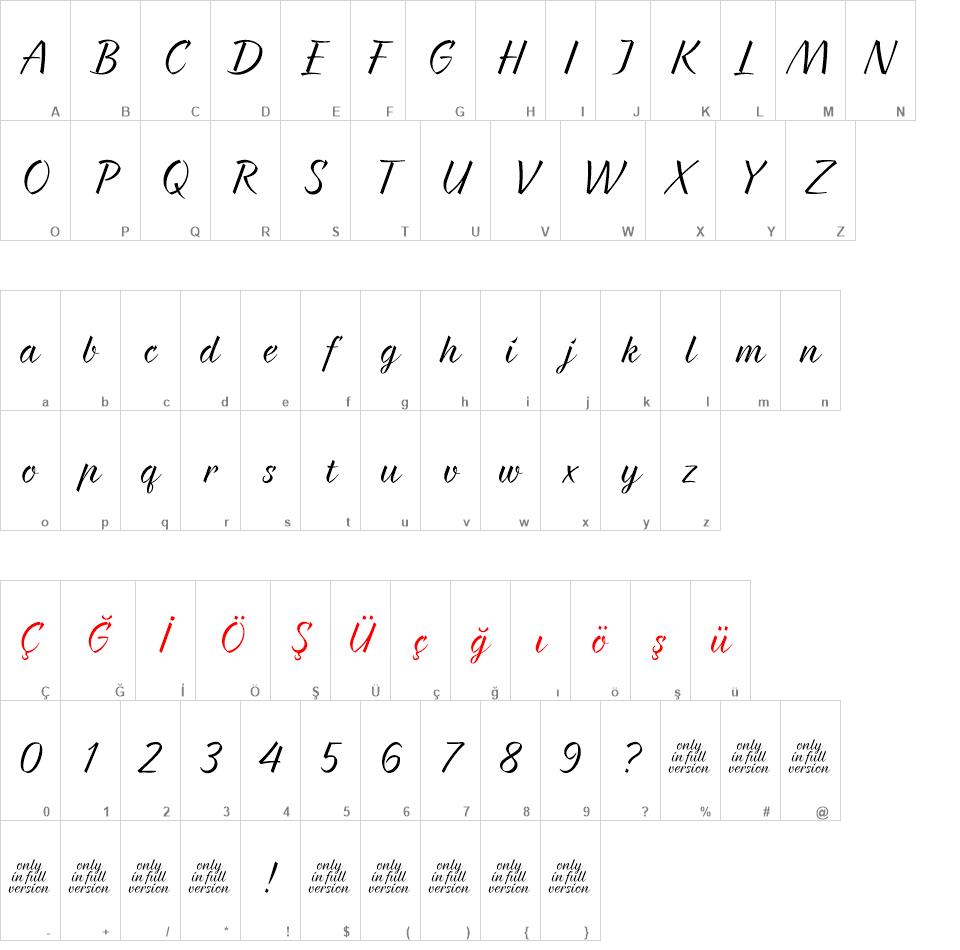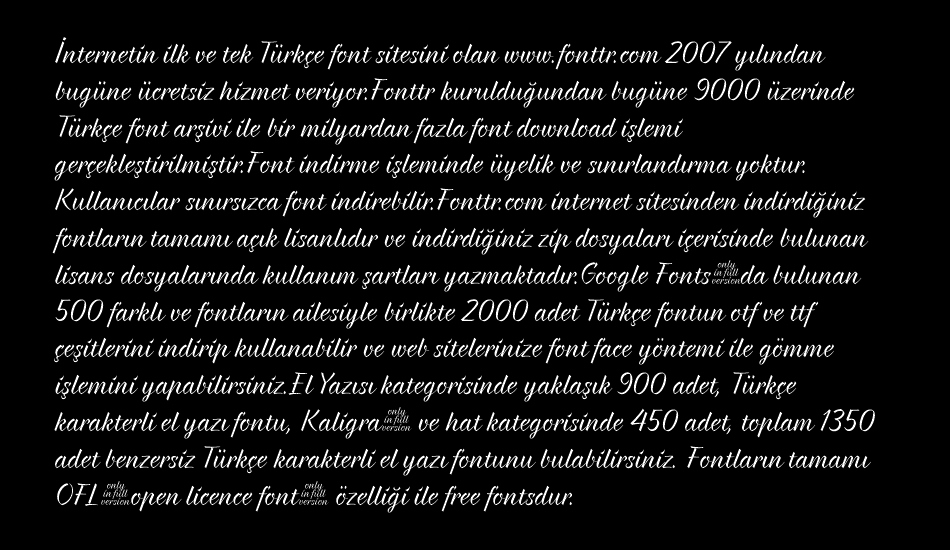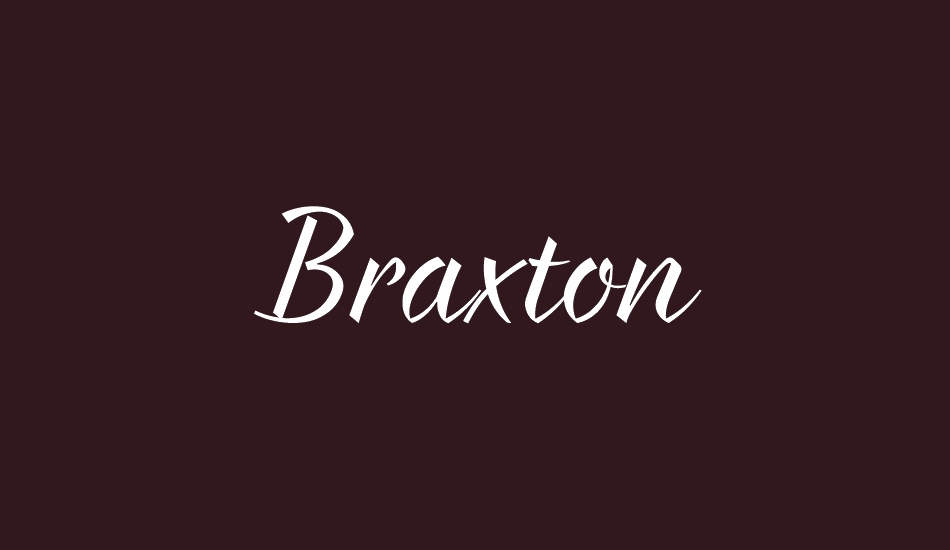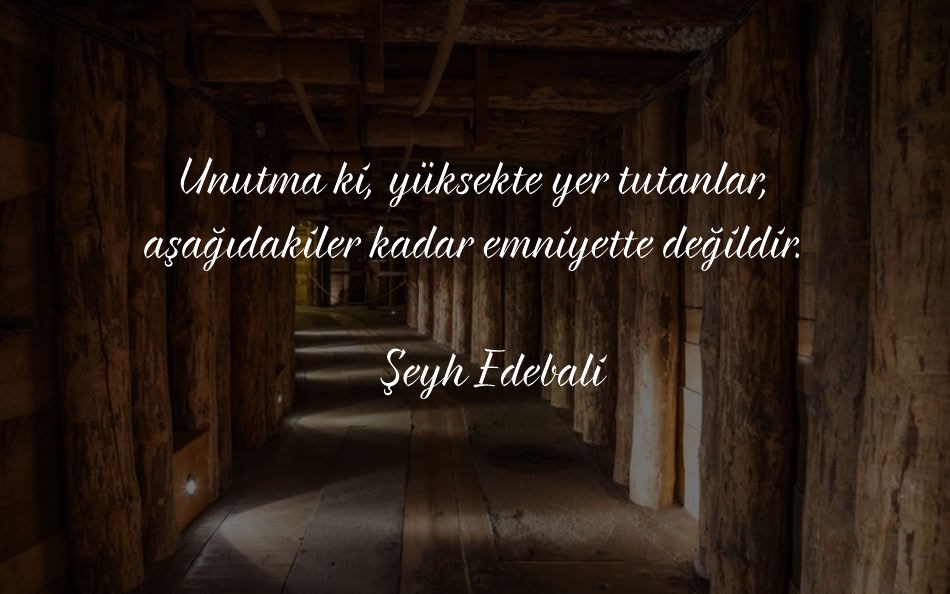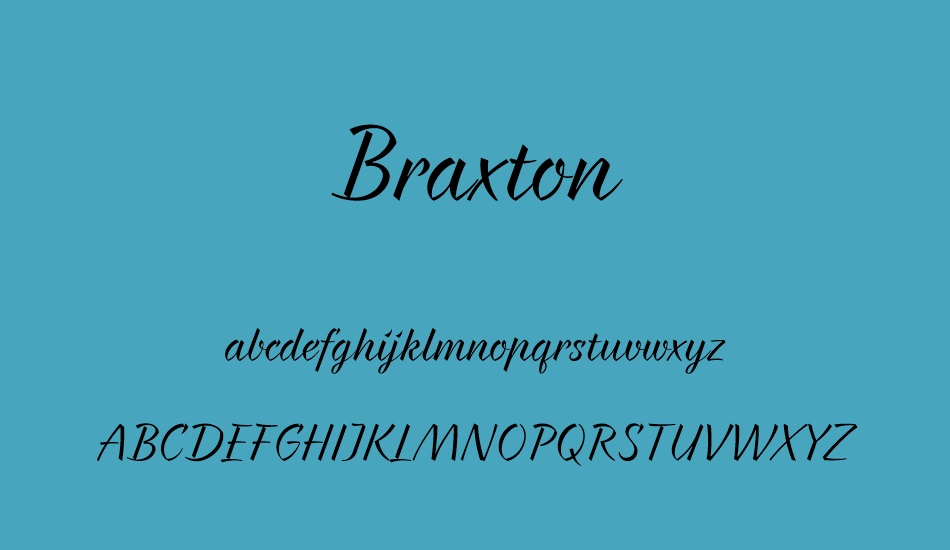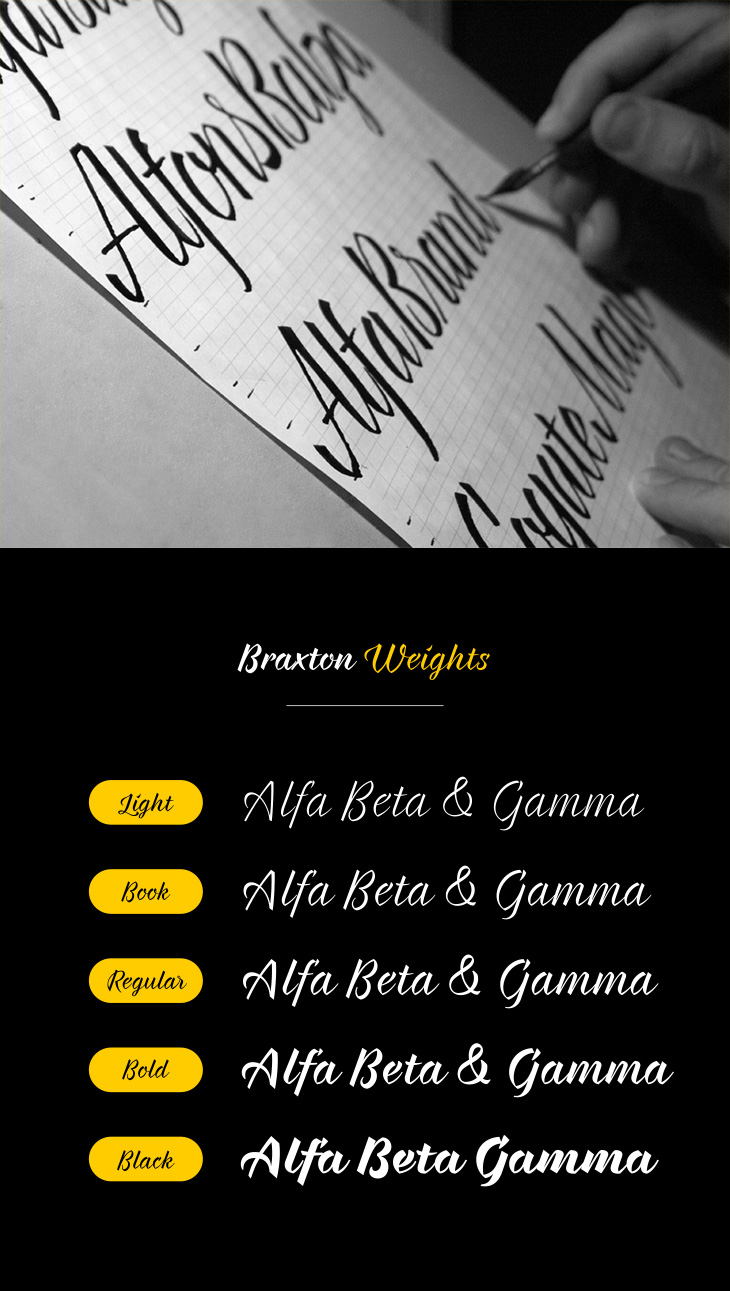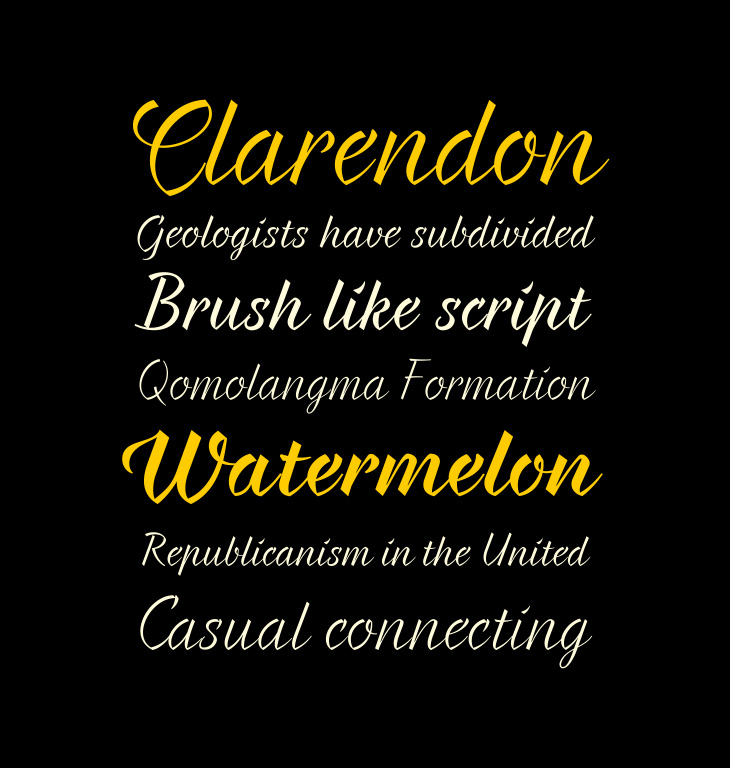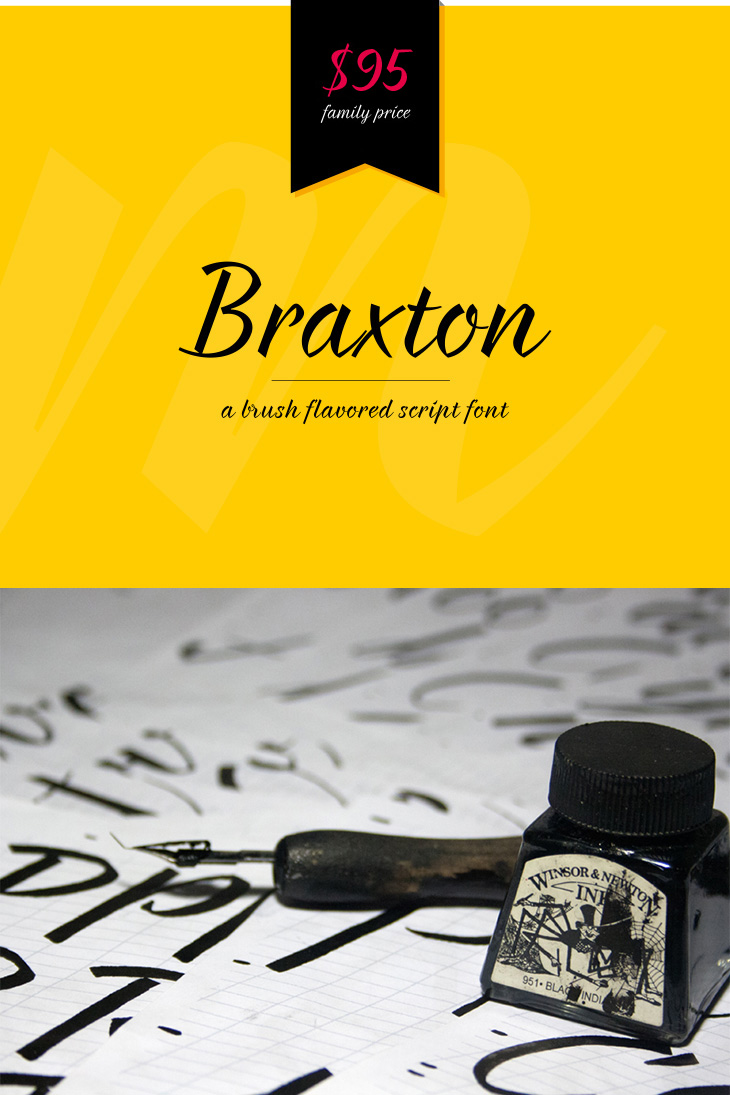
Braxton font
Yazı tipi ailesi, hem web hem de baskı tasarım alanları, iyi kalpli kaligrafik tasarımlar, optimize karakter aralığı gibi alanlarda mükemmel okunabilirliğe sahiptir.
Braxton, her boyuttaki başlıklara ve hem maksimum hem de minimum varyasyonlu metin bloklarına en uygundur. Yazı tipi stilleri, web, baskı, hareketli grafik vb. Her türlü grafik tasarım için geçerlidir ve tişörtler ve posterler, logolar gibi diğer öğeler için mükemmeldir.